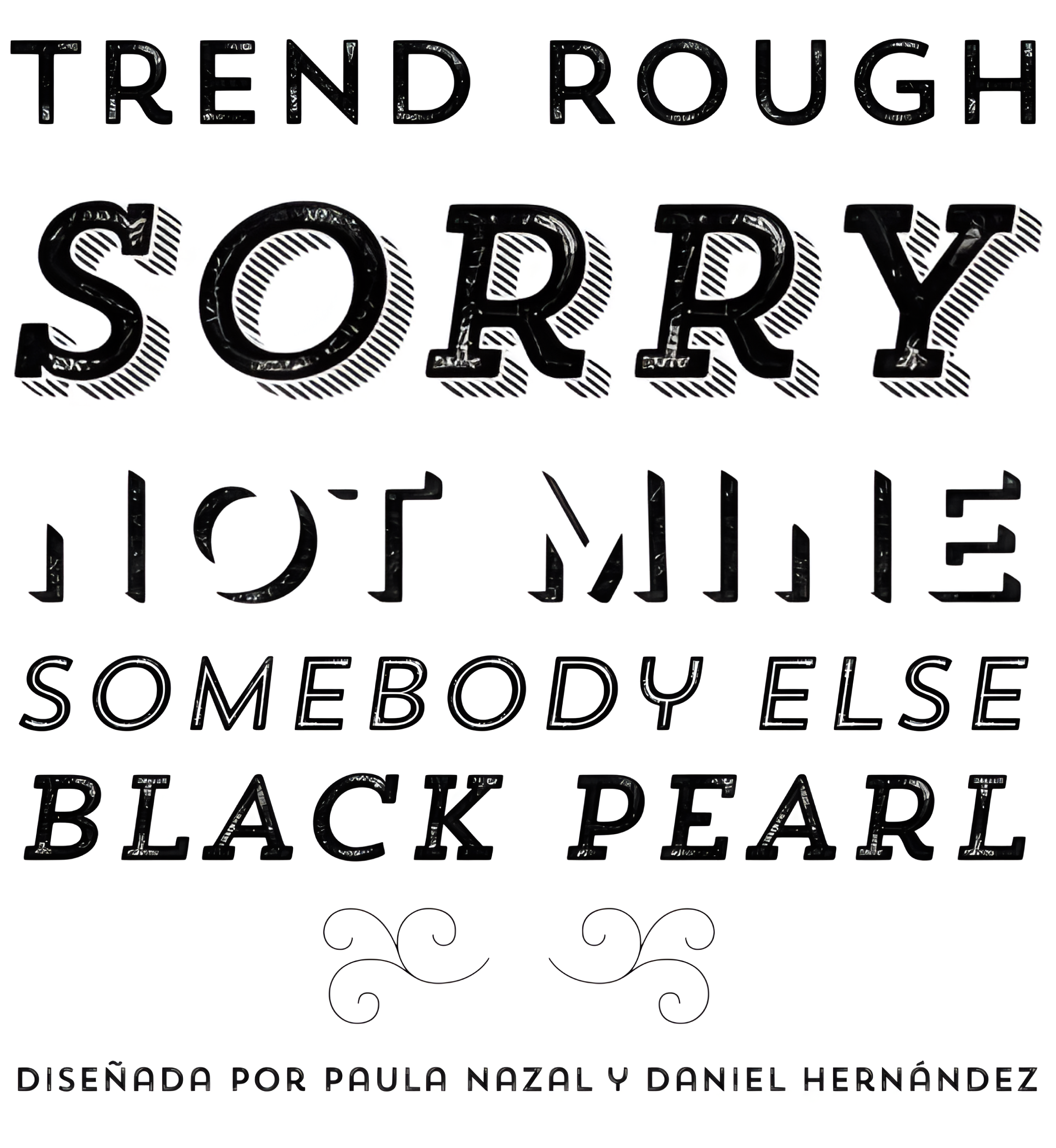
| Créditos | Paula Nazal Selaive, Daniel Hernández |
| Descripción | Trend; Trend Rough es un tipo de letra por capas, tomando como base una sans y una una fuente slab. Es el resultado de la observación, búsqueda y estudio de las últimas tendencias mundiales. Trend intenta captar la estética de la moda o incluso la moda misma, integrando elementos de una tendencia muy popular y actual. Es un tipo de letra diseñado para ser utilizado sin necesidad de añadirle nada externo, ya que cuenta con todos los componentes necesarios para ello. La tendencia es tendencia. |
| Clasificación | Títulos, Dingbats, Patterns |
| Familia(s) | Sans One, Sans One Italic, Sans Two, Sans Two Italic, Sans Three, Sans Three Italic, Sans Four, Sans Four Italic, Sans Five, Sans Five Italic, Slab One, Slab One Italic, Slab Two, Slab Two Italic, Slab Three, Slab Three Italic, Slab Four, Slab Four Italic, Slab Five, Slab Five Italic, Ornaments, Ornament Two, Words, Dingbats |